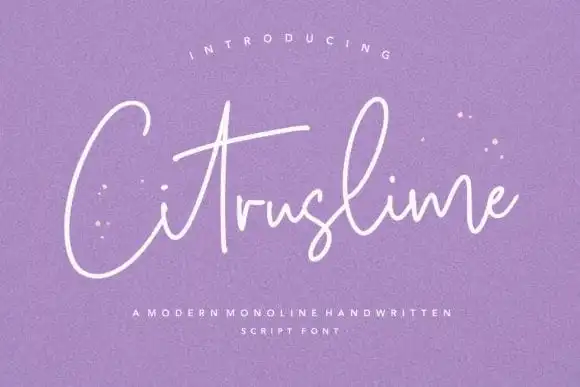
A Citruslime Handwritten Font é uma escolha perfeita para quem busca uma mistura única de simplicidade e autenticidade na sua tipografia. Moderna mas ainda assim genuína, essa fonte oferece um conjunto completo que inclui letras minúsculas e maiúsculas, números e pontuação. Seja para personalizar suas publicações no Instagram ou mesmo para projetos DIY de escritura artesanal, a Citruslime Handwritten Font irá transformar qualquer ideia criativa em uma verdadeira obra de arte. Este é um ótimo complemento para designers que buscam agregar estilo e personalidade sem comprometer a elegância da tipografia. Em contraste com o tradicional e moderno, essa fonte traz um toque único e encantador ao seu trabalho gráfico, tornando cada projeto único e de alta qualidade.